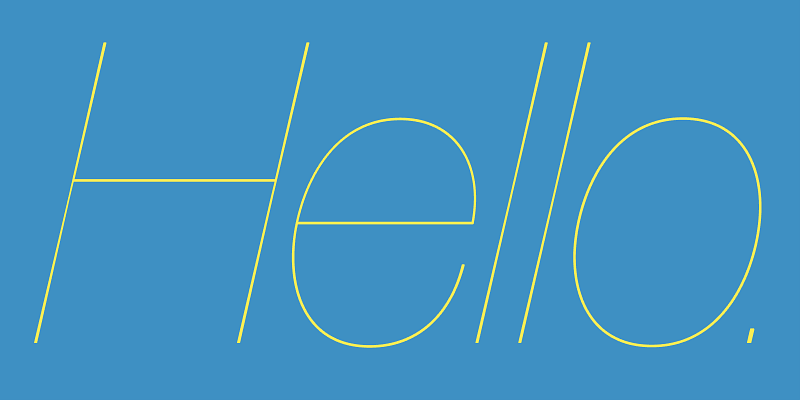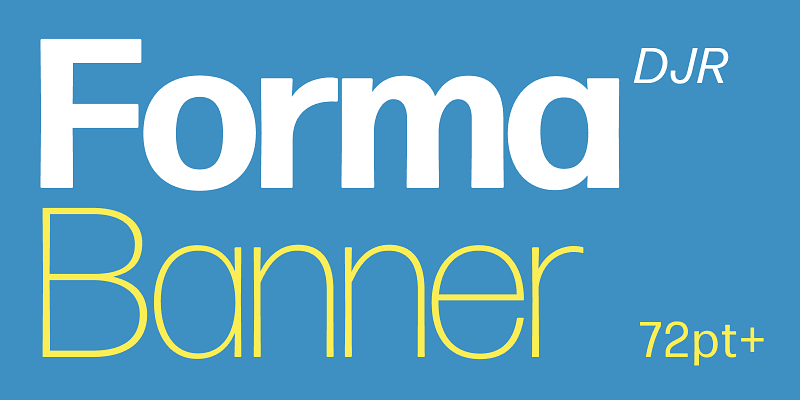
Die Forma DJR ist eine Wiederbelebung einer Älteren Grotesk (Neo Grotesque) von Aldo Novarese aus der späten Mitte des Jahrhunderts für die italienische Gießerei Nebiolo. In Zusammenarbeit mit Roger Black und Indra Kupferschmid befasste sich David Jonathan Ross mit den ursprünglichen Drucktypen aus Metall und interpretierte das Design als eine große Familie mit optischen Größen, abgerundeten Ecken und sich verjüngenden Stielen. Später wurde die Bandbreite an Schriftstärken um die Extreme „Hairline“ und „Black“ erweitert und als variabler Designraum neu konzipiert, mit Beiträgen von Ruggero Magrì.
David Jonathan Ross zeichnet Buchstaben aller Formen und Größen für kundenspezifische und Sortiments-Schrift-Designs in seinem Studio in den Wäldern von West Massachusetts. Ursprünglich aus Los Angeles begann er Schriften am Hampshire College zu zeichnen und ging 2007 zum Font Bureau, wo er seine Fertigkeiten in der Bézier-Bearbeitung ausbaute. Jetzt veröffentlicht er seine Schriften-Designs bei seinem eigenen Schriftanbieter DJR, arbeitet mit Type Network an Projekten und entwickelt ungewöhnliche Display-Schriften für seinen Font of the Month Club.